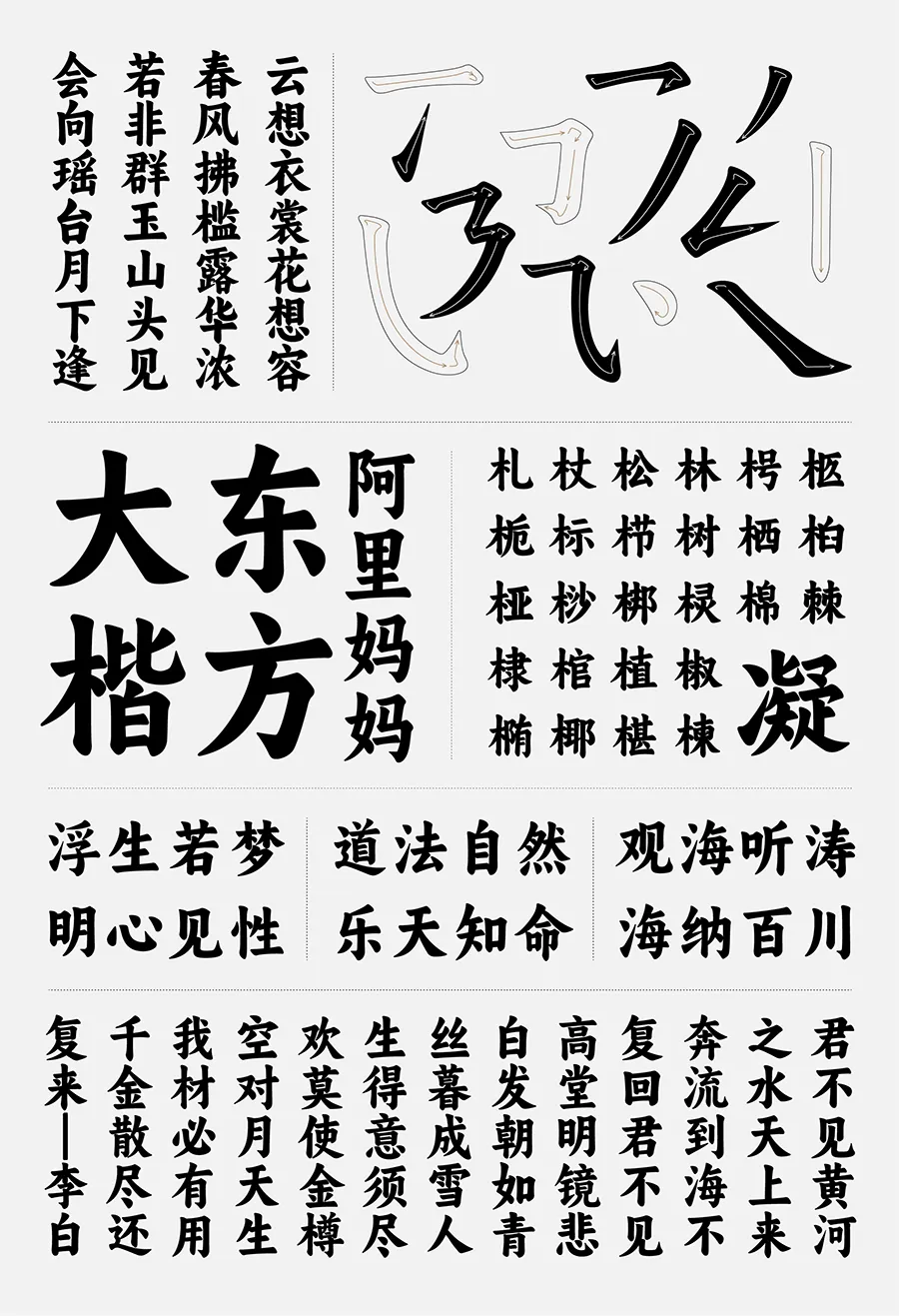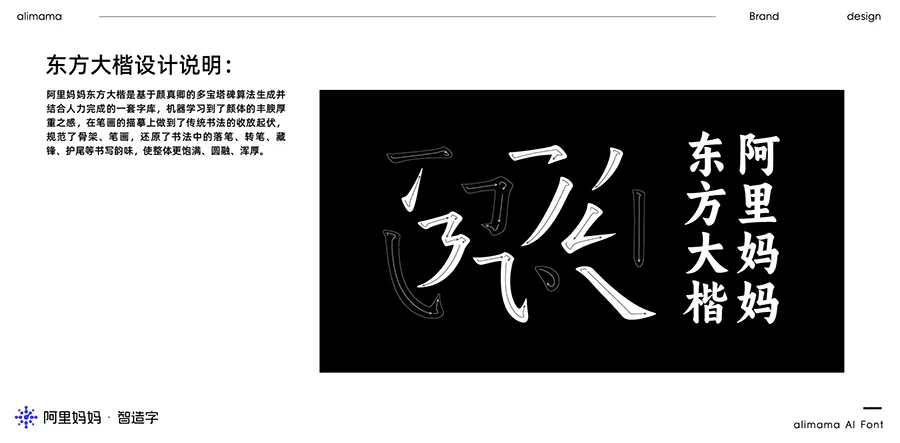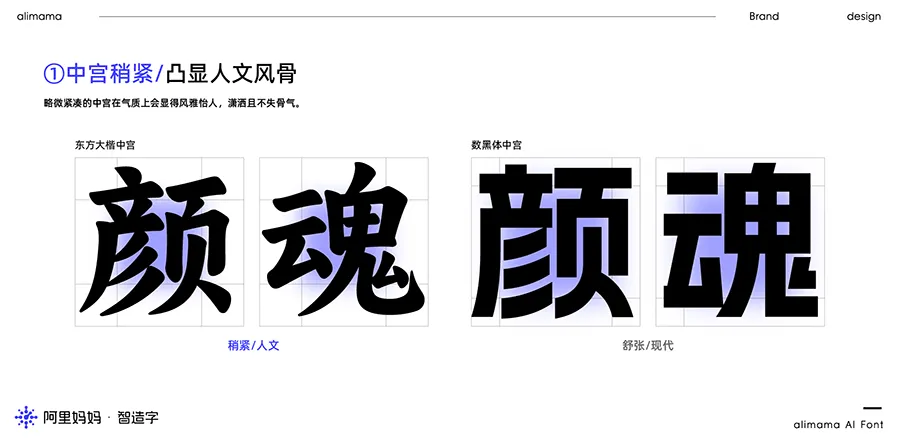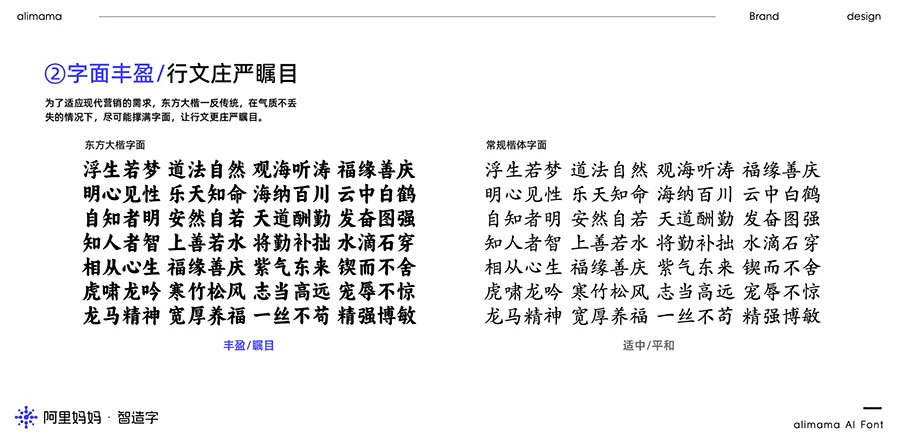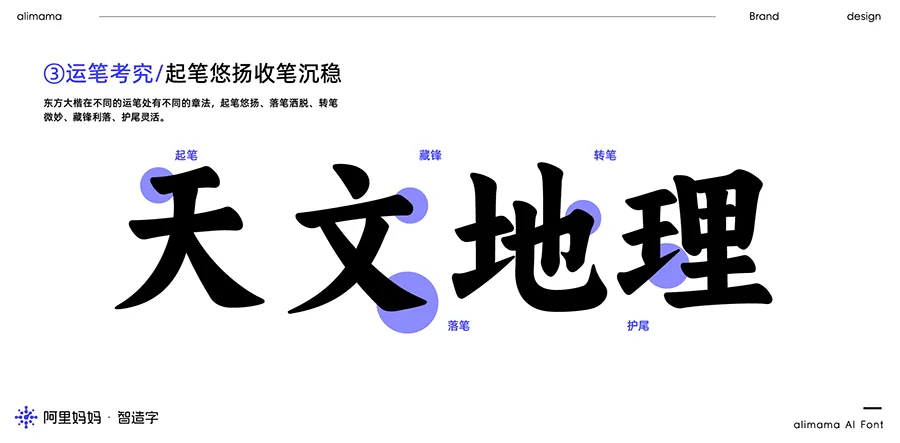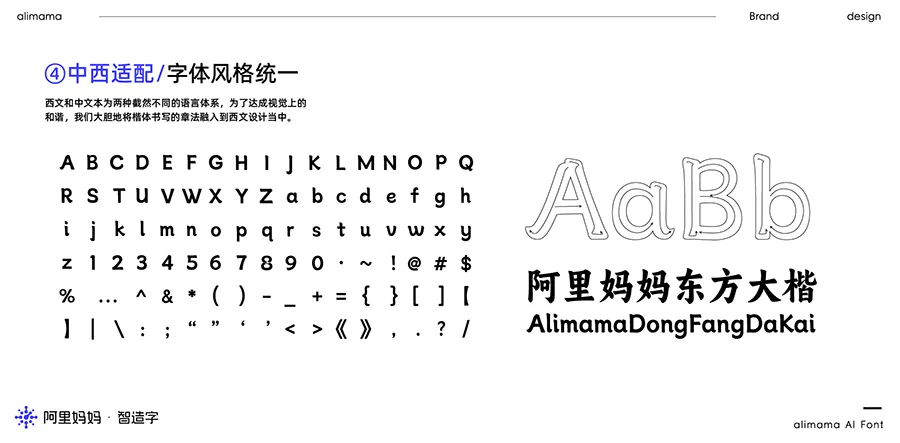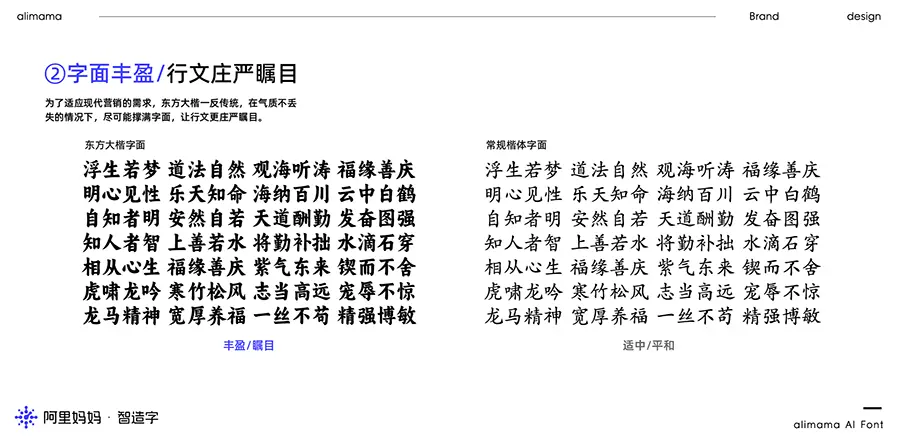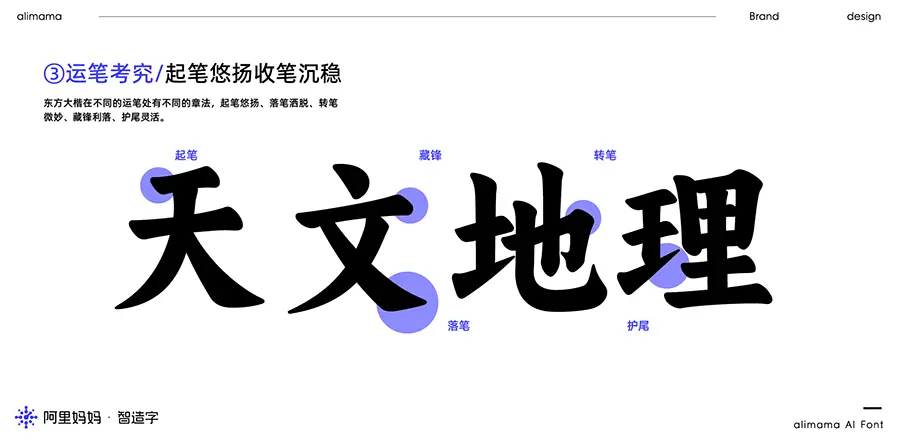
阿里媽媽東方大楷是基於顏真卿的多寶塔碑算法生成並結合人力完成的一套字庫,機器學習到了顏體的豐腴厚重之感,在筆畫的描摹上做到了傳統書法的收放起伏,規範了骨架、筆畫,還原了書法中的落筆、轉筆、藏鋒、護尾等書寫韻味,使整體更飽滿、圓融、渾厚。
阿里媽媽東方大楷為中文簡體字庫,收納的中文字符包括但不限於GB2312,共計6763個漢字;英文大小寫(含全角、半角、合體字等)共105個;常用標點符號共175個,總計7043個字符。